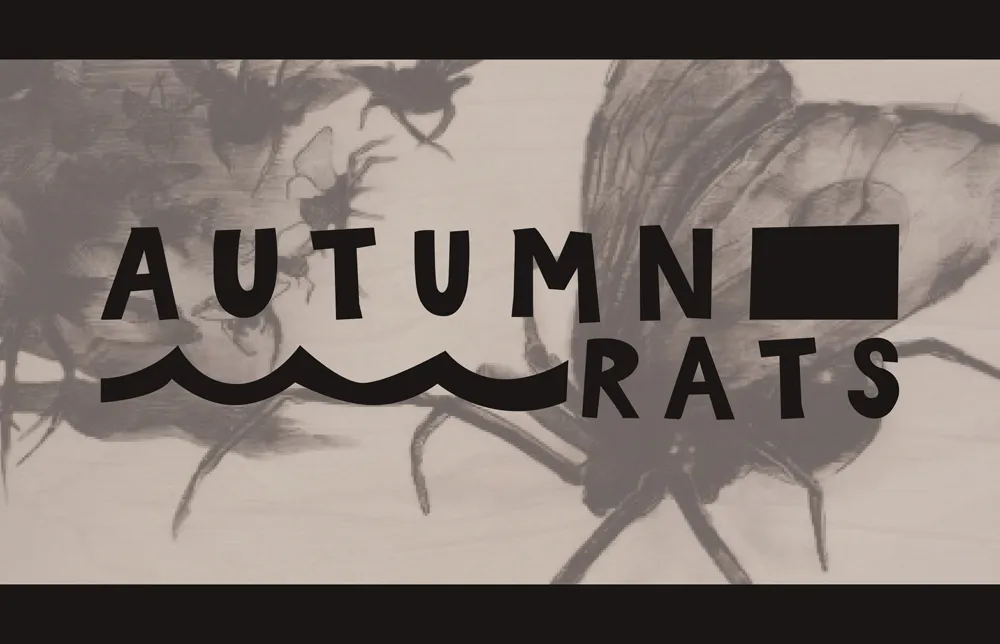
Autumn Rats font – Fonte Grátis
Autumn Rats font
A fonte Autumn Rats é uma escolha perfeita para aqueles que buscam elegância e simplicidade no design digital. Idealmente projetada como uma fonte sans-serif, ela oferece uma aparência moderna e clara, sendo especialmente atraente em designs de texto, banners ou qualquer projeto online onde você precisa de um aspecto leve e não menos formal. Projetada pelo designer Hamilton, Autumn Rats foi cuidadosamente desenvolvida para manter uma consistência harmônica entre linhas curvas suaves e espaçamento equilibrado. Com sua composição fluida e elegante, ela é perfeitamente adaptável a uma variedade de estilos e aplicações gráficas sem deixar de ser funcional ou robusta. Seja para criar um site responsivo, adicionar um toque sofisticado a um layout web ou imprimir seu próximo projeto editorial digital, Autumn Rats proporcionará uma experiência visual agradável. Através do seu equilíbrio entre simplicidade e modernidade, essa fonte é perfeita para qualquer profissional que busca manter sua identidade visual ao avançar em design online.